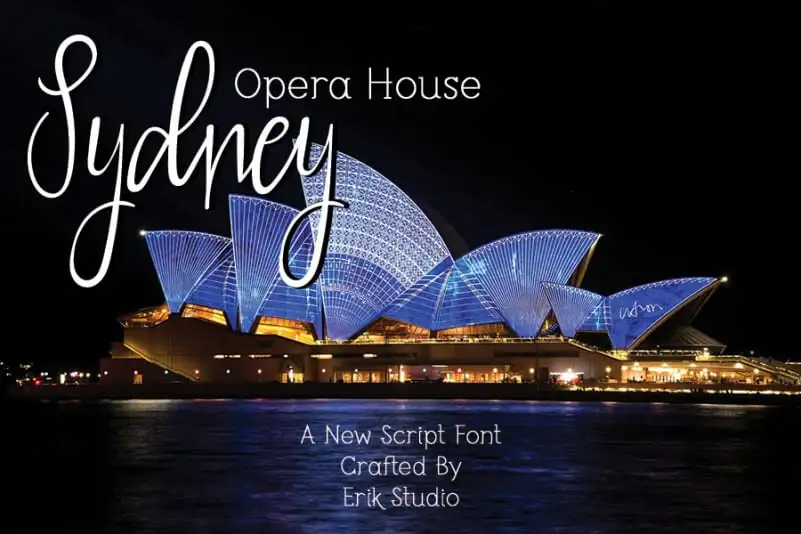
Sydney Script Font – Download Grátis
A Sydney Script Font é uma fonte escrita a mão única e incrivelmente criativa. Foi meticulosamente projetada para transformar seu próximo projeto em algo realmente memorável, elevando-o ao nível máximo de originalidade e beleza. Essencialmente, essa fonte permite que você expressa seus sentimentos e ideias de maneira autêntica e personalizada, dando vida à sua mensagem. Seja um cartão de visita de negócios ou uma ilustração para seu próximo projeto gráfico, a Sydney Script Font será sua melhor aliada em transformar pensamentos em objetos visíveis. Com um estilo elegante e fluido, essa fonte escrita a mão é perfeita para quem valoriza design único. Com a designer Erik Studio por trás dela, esta fonte está certificada como uma das melhores opções na categoria de Fontes Escritas a Mão. É o tipo de fonte que você gostaria de adicionar ao seu arsenal de ferramentas gráficas, para criar mensagens que são inegavelmente suas próprias.